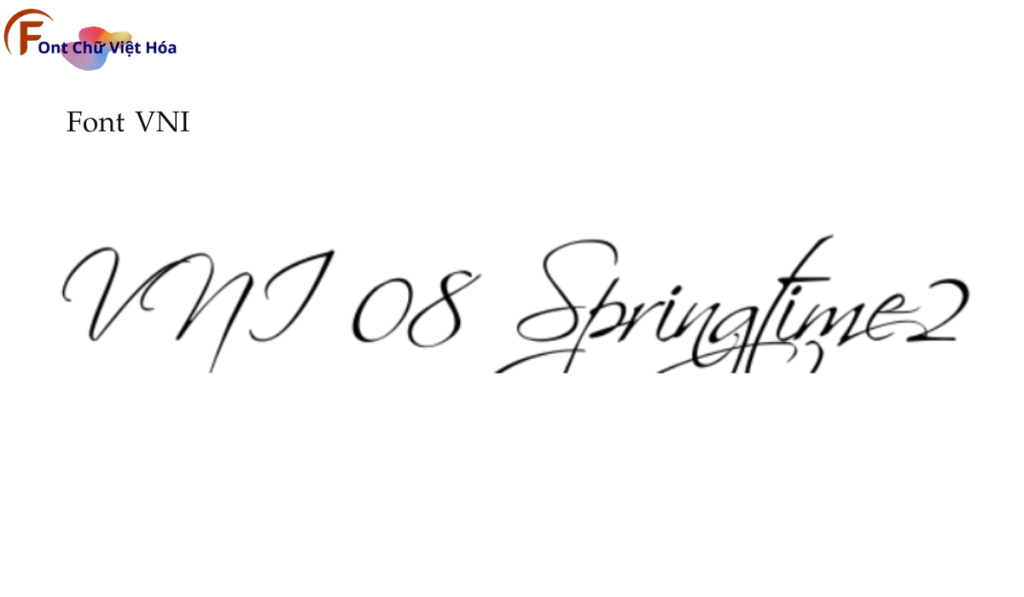
Font VNI Springtime Việt Hóa
Kiểu chữ: Chữ viết tay
Font VNI Springtime Việt Hóa, thuộc bộ font VNI, được tạo ra nhằm mang đến sự sáng tạo và độc đáo, phù hợp cho các dự án thiết kế như thiệp mời, bìa sách, và các sản phẩm thủ công. Với các nét chữ mềm mại và độ dày đồng đều, Font VNI Springtime Việt Hóa không chỉ dễ đọc mà còn tạo nên cảm giác nghệ thuật và tinh tế. Font này mang phong cách nhẹ nhàng và thanh lịch, lý tưởng cho các thiết kế cần sự tinh tế và sáng tạo. Việc Việt hóa font giúp người dùng dễ dàng tích hợp vào các thiết kế tiếng Việt, mang lại sự tiện lợi và nâng cao tính thẩm mỹ.